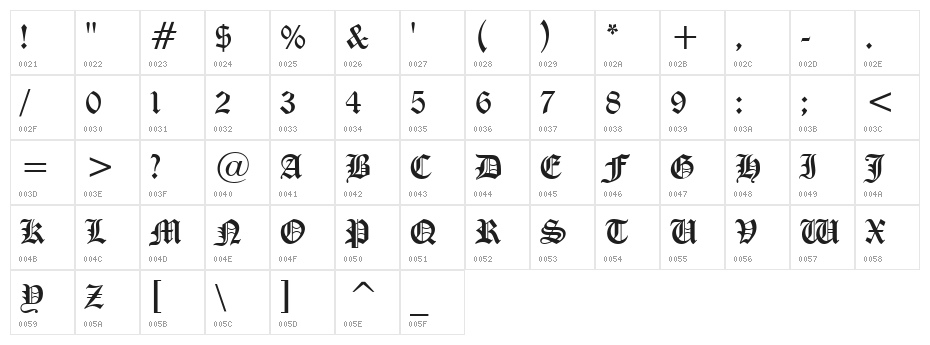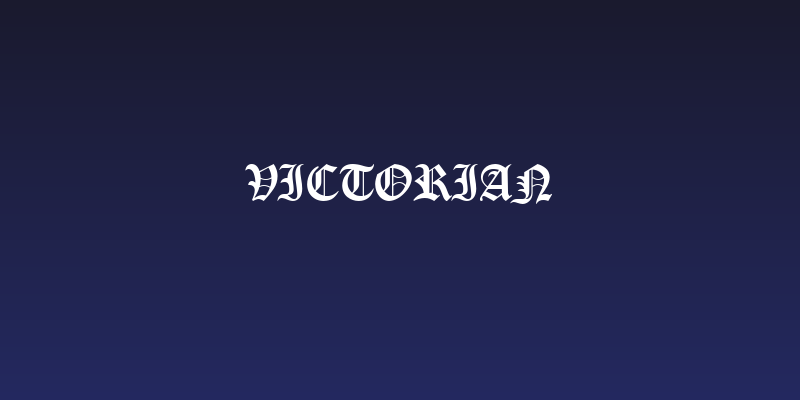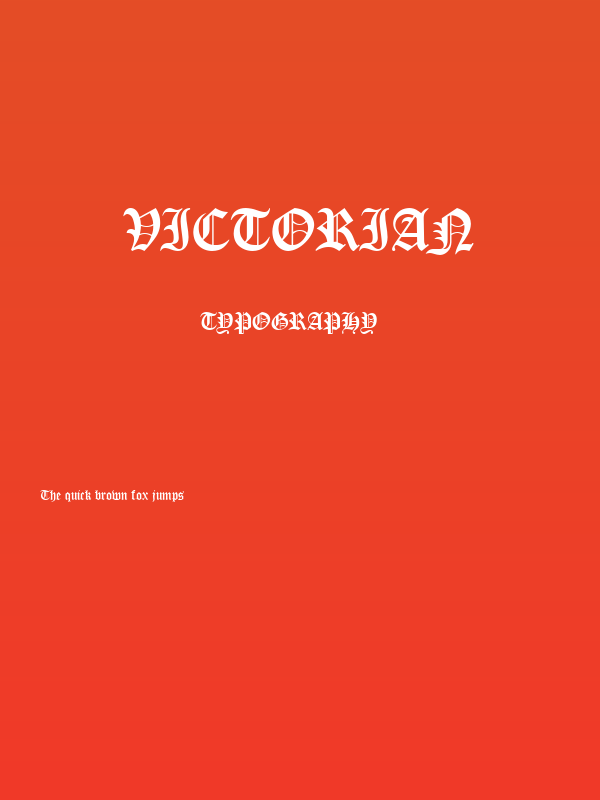
Victorian Font
✎ Gothic
| 用途 | Headlines, Logos, Decorative text |
| おすすめプロジェクト | Ideal for vintage-themed designs, historical publications, theatrical posters, or any project requiring a touch of classic elegance. |